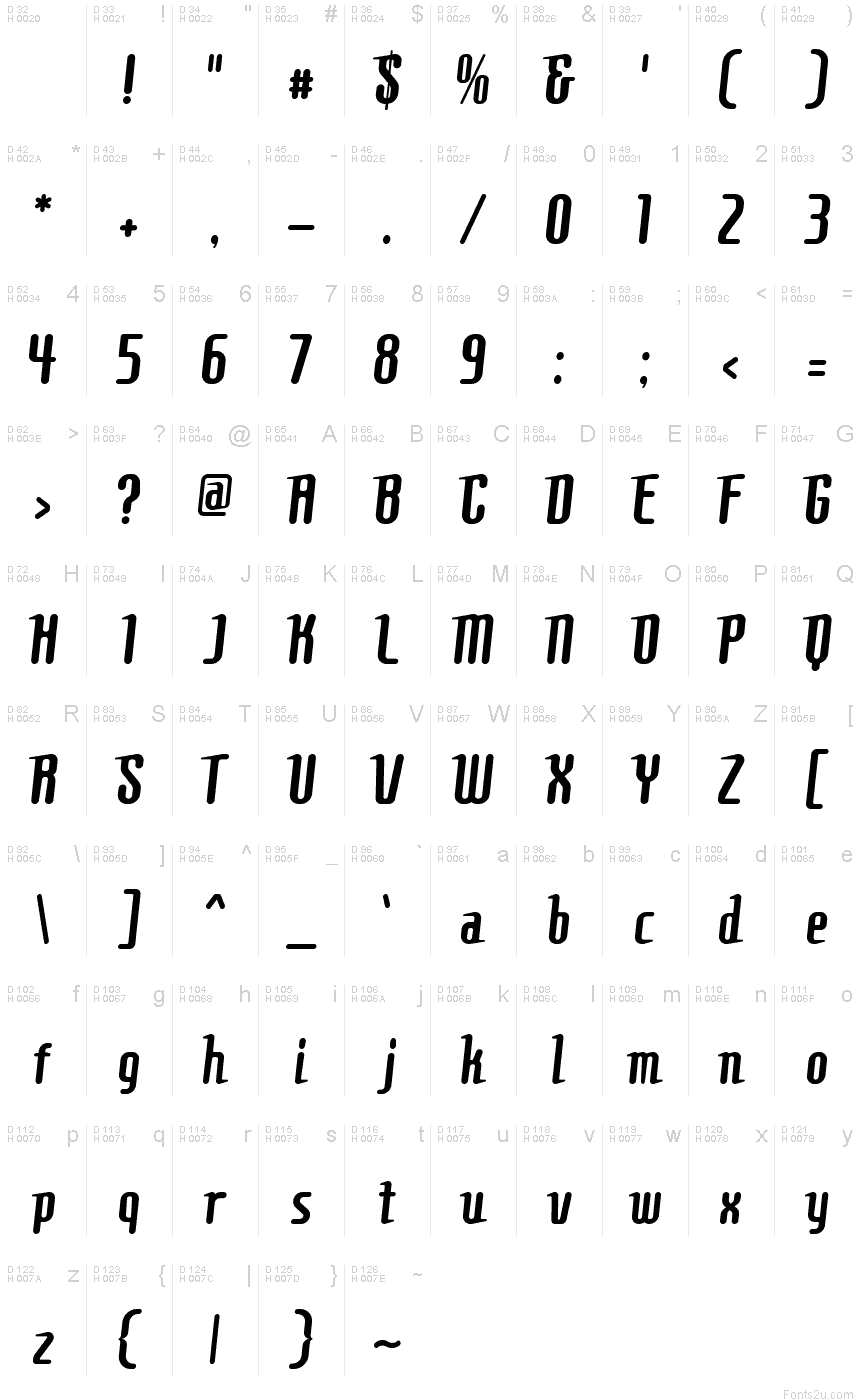
Comons od Masato Shimojimy z Design studio creation to nowoczesny, darmowy krój pisma typu display o odważnym, pochylonym charakterze. Jego grube pociągnięcia, zaokrąglone rogi i subtelny, niemal odręczny przepływ nadają mu energię ręcznie malowanych szyldów, przy jednoczesnym zachowaniu czystej spójności geometrycznego bezszeryfu. Litery wydają się ciężkie i nasycone, jakby zostały nakreślone jednym, pewnym ruchem, tworząc silny rytm, który czyta się szybko i wyraziście.
Jako darmowy font, Comons świetnie sprawdza się w brandingu, grafikach sportowych, plakatach, wyrazistych opakowaniach, gadżetach i przyciągających wzrok nagłówkach. Pochylenie w przód sugeruje szybkość i dynamikę, co czyni go naturalnym wyborem dla energicznych projektów lub estetyki streetwearowej. Stosuj go w dużym rozmiarze, aby pozwolić jego płynnym krzywym i gęstym formom wybrzmieć, a w tekstach uzupełniających łącz go z prostym, neutralnym bezszeryfem, aby wyeksponować logotyp lub tytuł.